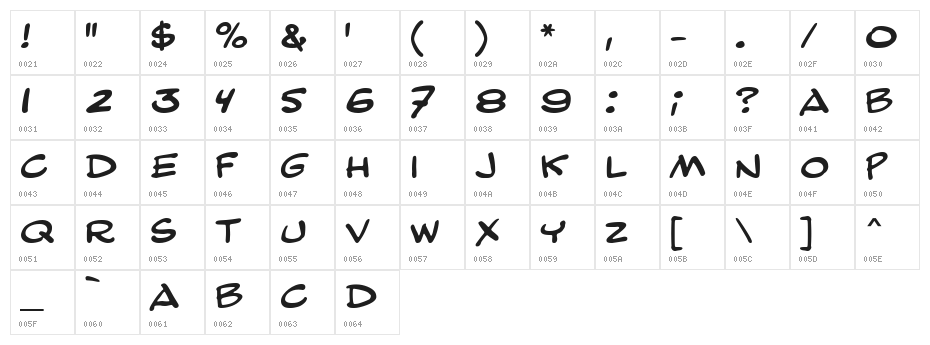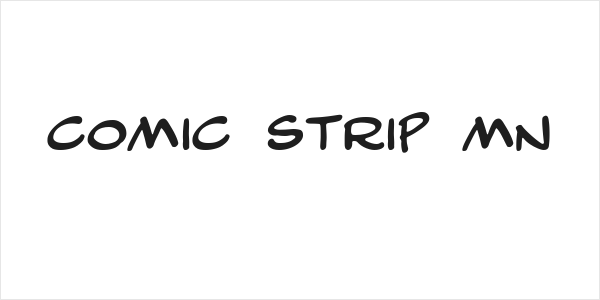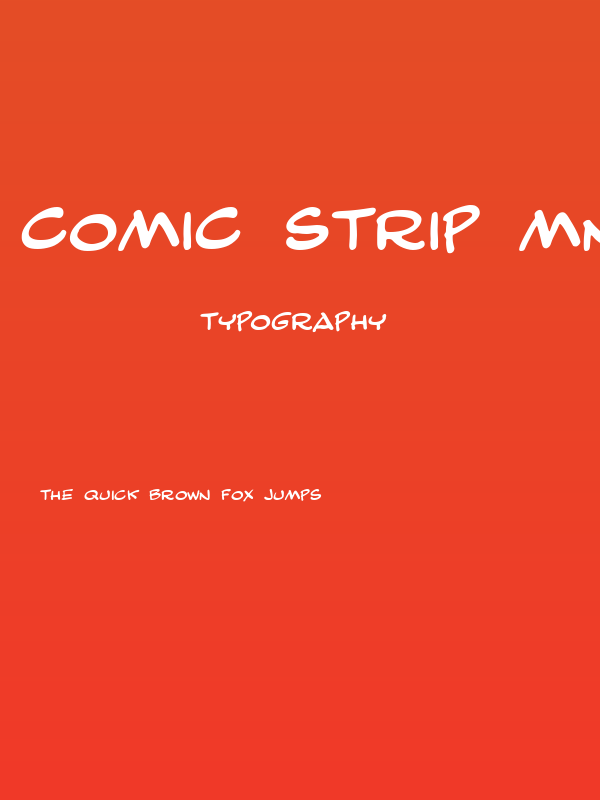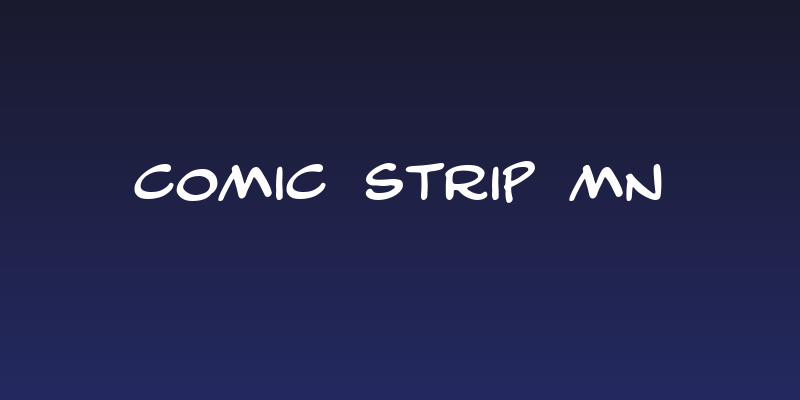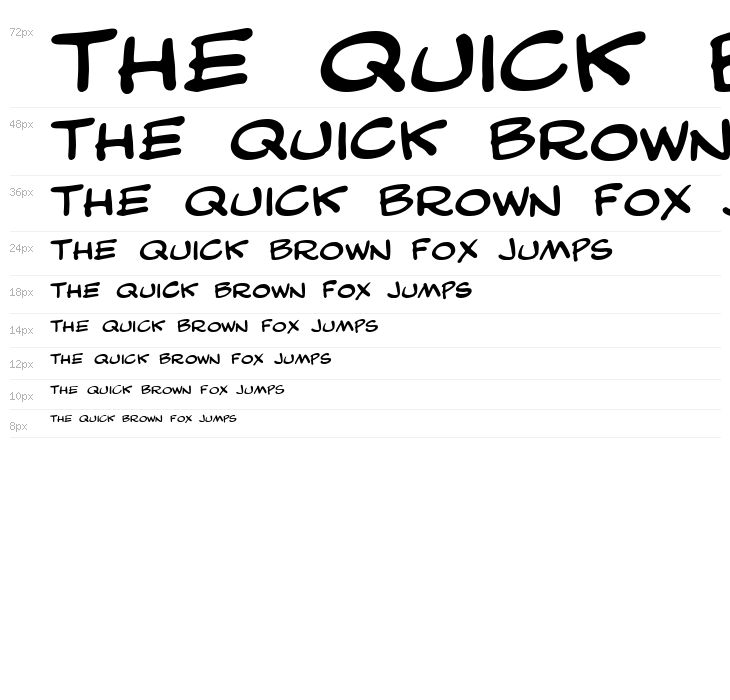
Comic Strip MN Font
| الفئات | Comic |
| النمط العام | Playful |
| حالة الاستخدام | Headlines, Logos, Informal Text |
| مشاريع مقترحة | Ideal for comic books, children's books, playful branding, and informal invitations. |